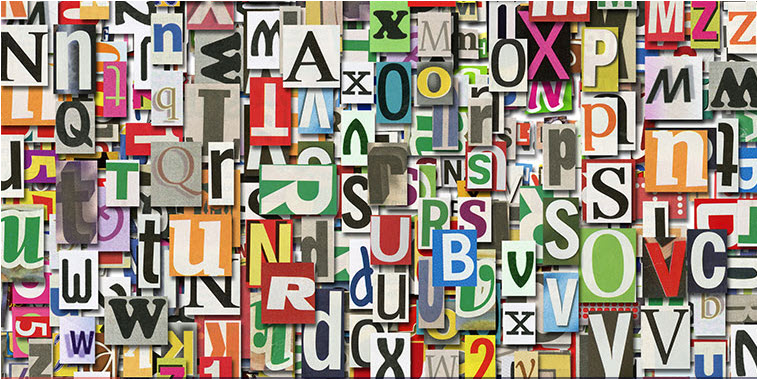
Шрифты – это вершина дизайна. И их разработкой всегда занимались только очень крутые дизайнеры. Сама история европейских шрифтов связана с именами Леонардо да Винчи и Альбрехта Дюрера, которые внесли свой огромный вклад в разработку шрифтов типа антиквы, известных ещё со времени знаменитой колонны Трояна. Что же до кириллического алфавита – то с ним всё сложнее. Наш алфавит пережил массу трансформаций со времен Кирилла и Мефодия, а в результате мы имеем начертания букв в кириллице, которые очень сложно компоновать в шрифтовые плакаты.
Посмотрев этот класс, вы узнаете, какие принципами нужно руководствоваться при построении шрифтовых композиций, каких ошибок избегать и как при помощи шрифта сделать ваше сообщение не только гармоничным, но и читабельным. Более того, прямо на классе мы разрушим несколько популярных мифов, которые сильно мешают работе. Например, о том, что нельзя использовать больше двух шрифтов в одном макете. Вместо этого вредного правила, вы узнаете, какие именно шрифты можно запросто компоновать, почему никогда не получится просто перевести на русский шрифтовые постеры на латинице и какой шрифт – по-настоящему вечный.
Посмотрев этот класс, вы:
Узнаете историю шрифта от Египта – до нашего времени.
Рассмотрите основные типы шрифтов: серифы/антиквы, гротески и брусковые.
Узнаете об истории появления самых популярных шрифтов Helvetica и Times.
Познакомитесь с великими дизайнерами нашего времени, которые внесли вклад в развитие культуры шрифта.
Научитесь использовать шрифты грамотно.
2.Краткая история письменности
3.Serif - Антиква
4.Sans Serif - Гротеск
5.Slab - Брусковый
6.Декоративные шрифты
7.Рукописные шрифты
8.Русский & Nerusskiy
9.Расстояния между знаками
10.Нарушая правила